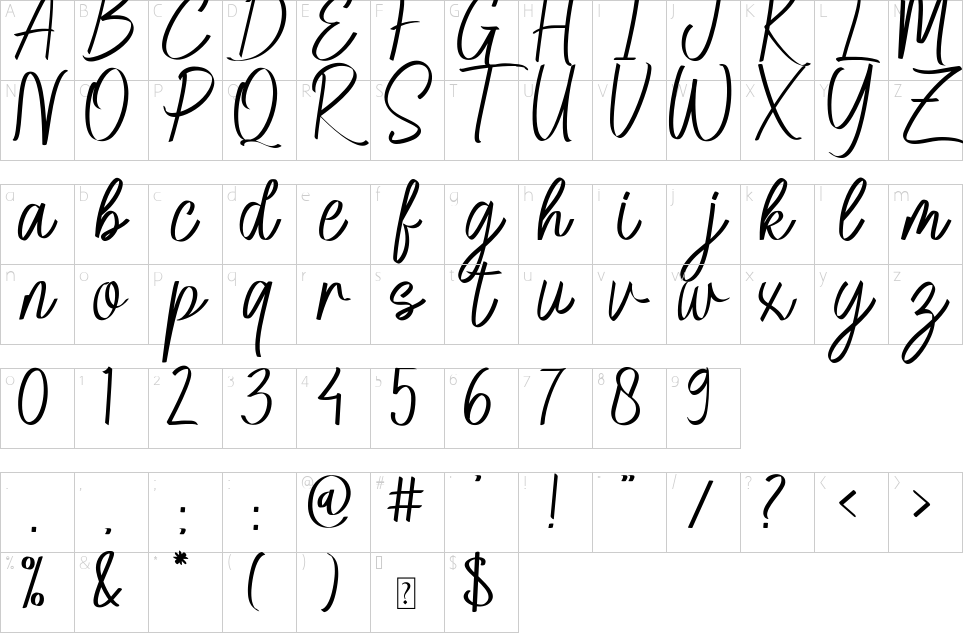
Agia Valley Font – Download Grátis
A Agia Valley Font é uma elegante opção para aqueles que buscam um visual atraente e natural em suas criações digitais. Desenhada pelo designer anônimo da StringLabs, esta fonte é ideal para designers gráficos, escritores, e até mesmo para pessoas que simplesmente adoram uma boa fonte no seu dia a dia. Com seu design cuidadosamente pensado e com características suaves e fáceis de usar, a Agia Valley Font é uma escolha excelente para projetos de texto em um range de ambientes, desde websites até aplicativos e impressões. Sua versatilidade e facilidade de uso tornam-na uma opção agradável para o design gráfico, sem deixar de lado a beleza natural que a caracteriza. Descubra a beleza da Agia Valley Font e faça seu design soar ainda mais único.